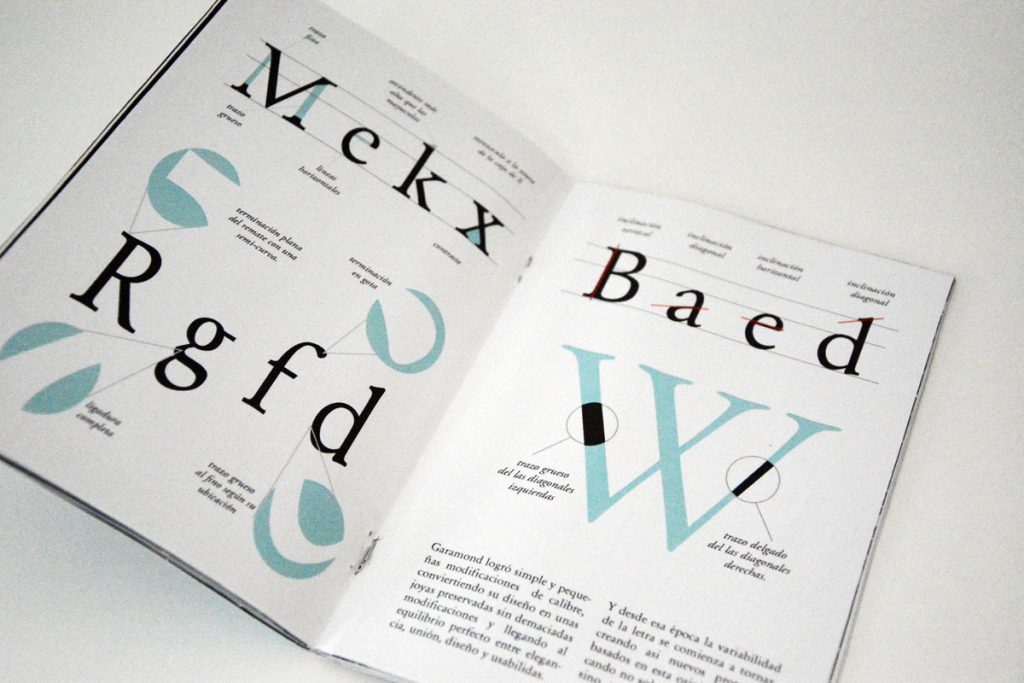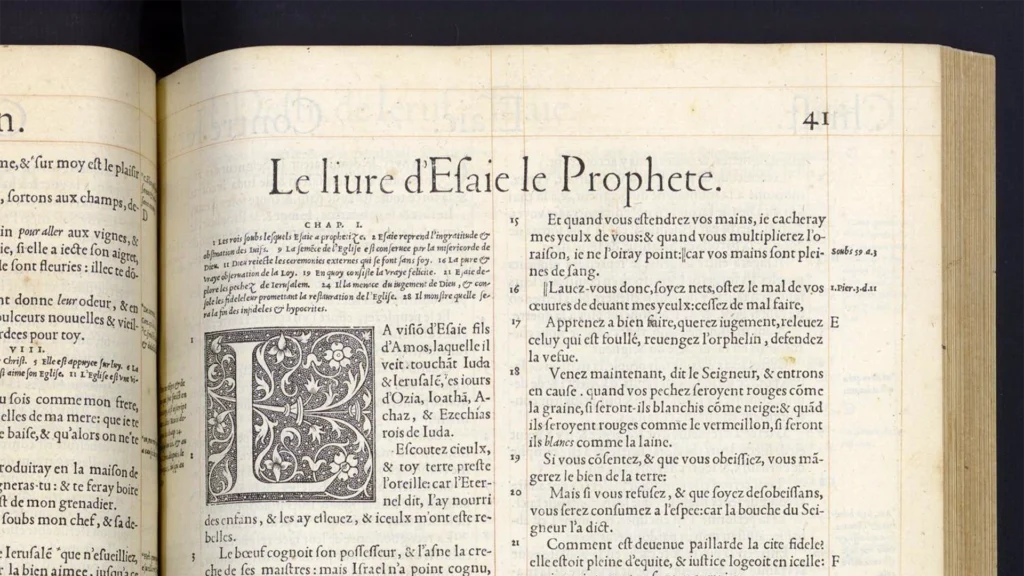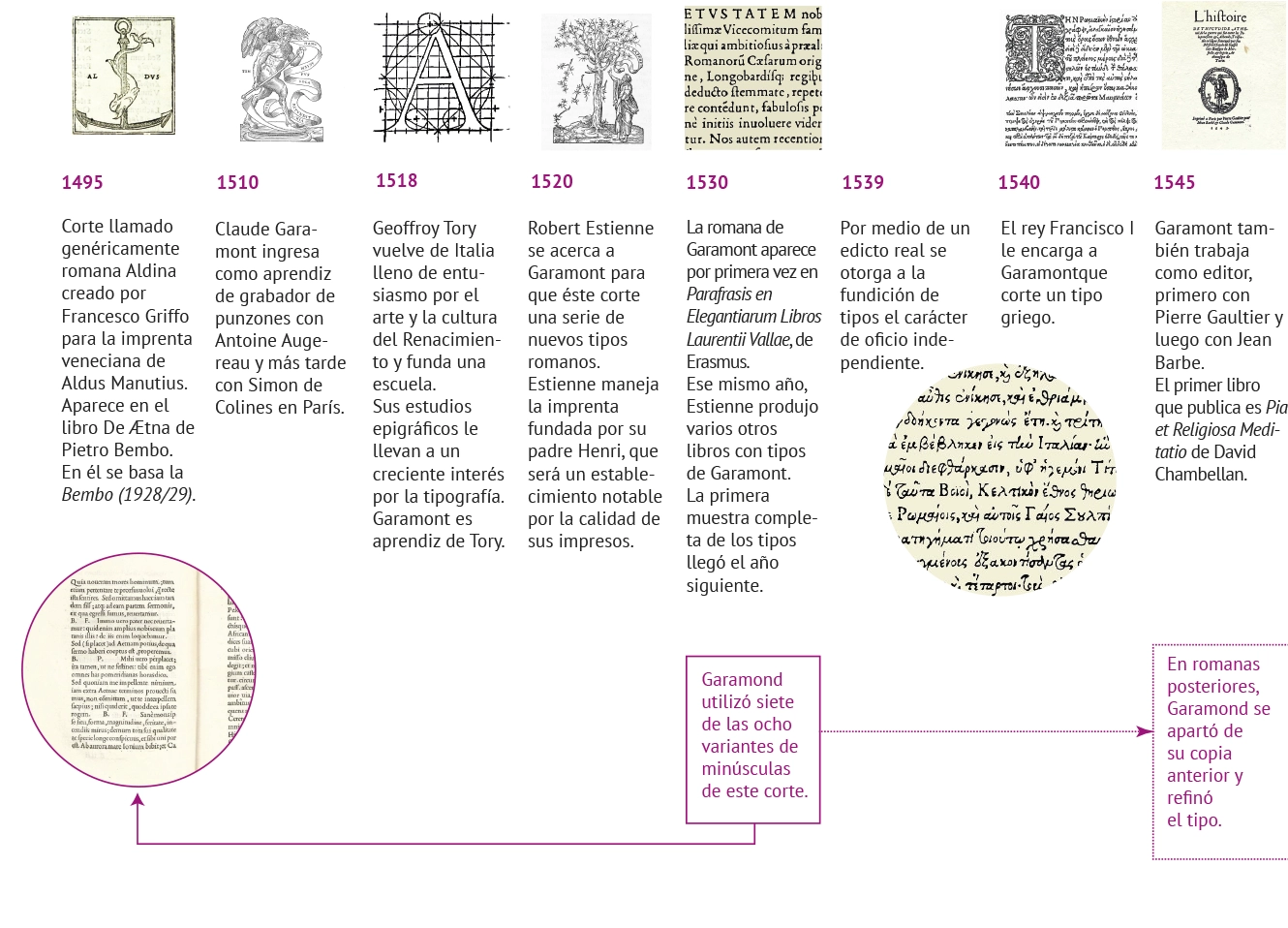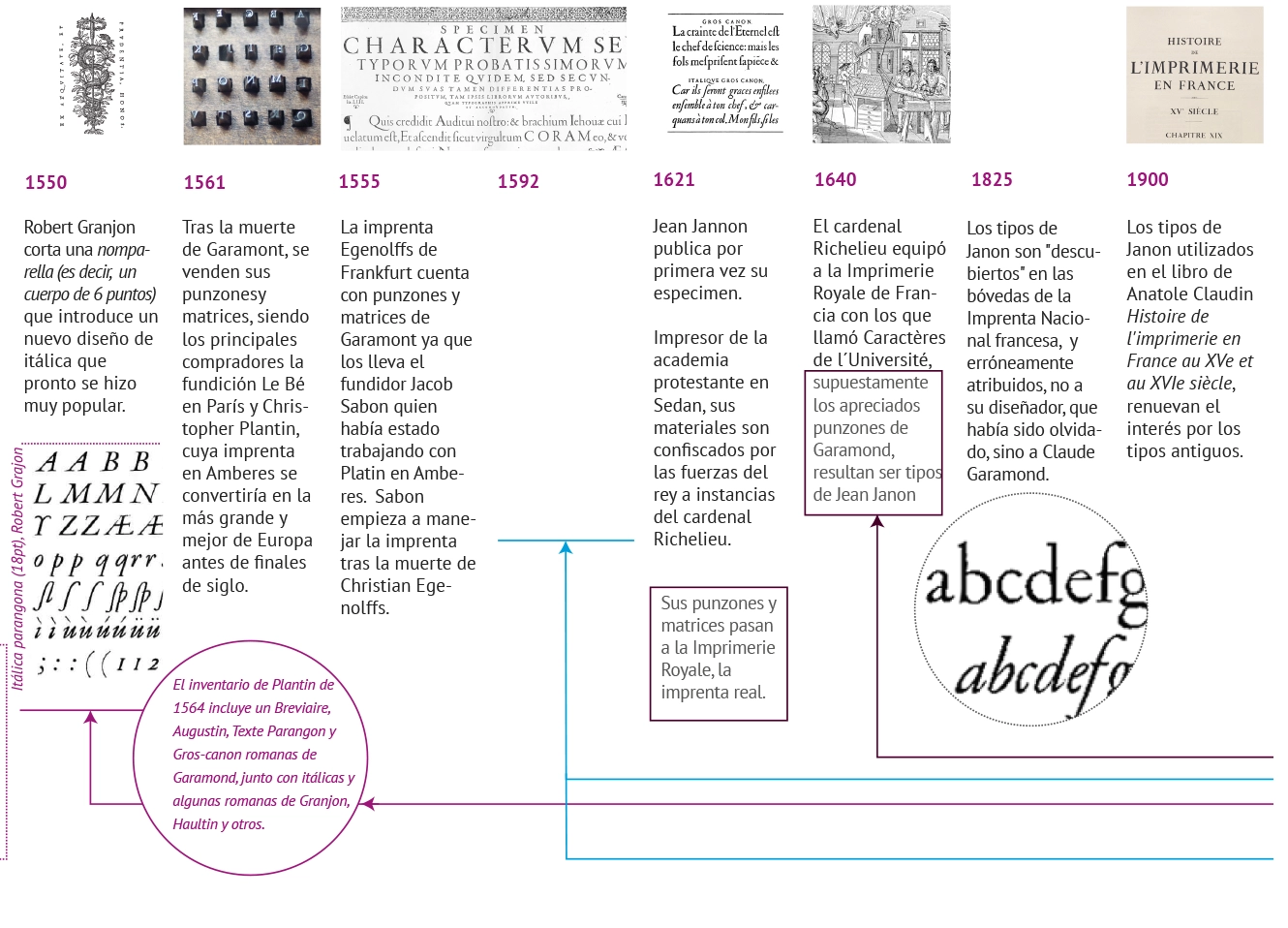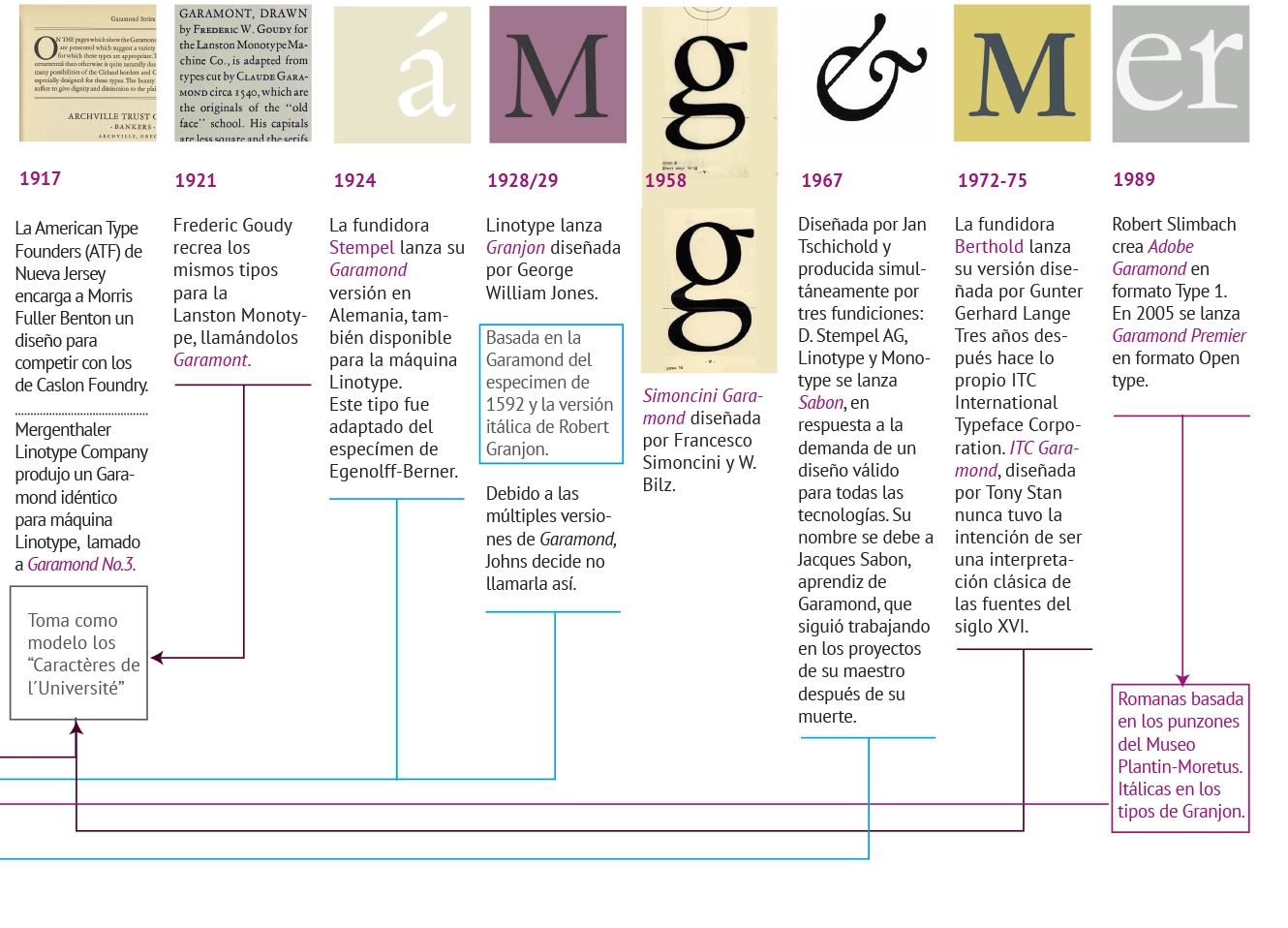
Hay tantas versiones de Garamond que nos es difícil encarar un artículo sin riesgo de dejar afuera información relevante. Aquí intentamos reunir cierta información acerca de su genealogía para dar cuenta de las herencias así como de las traducciones, confusiones y adaptaciones que jalonan su historia.
Garamond
Los tipos que actualmente llevan el nombre Garamond hacen referencia al gran punzonista francés del siglo XVI llamado Claude Garamont. Ha lo largo del tiempo, han tenido siempre gran demanda y, por lo tanto, están disponibles en una variedad de versiones de diferentes fundiciones. Estas muchas versiones no siempre conservan características del original. Esto es un factor que desconcierta y dificulta su identificación tal como se desarrolla en el artículo Garamond vs. Garamond.
En muchos casos, sería más apropiado el término más genérico de Garalda para referirse a estas fuentes. En particular, muchos resurgimientos de Garamond de principios del siglo XX toman como modelo el trabajo de un punzonista posterior a Garamond llamado Jean Jannon. Aunque su trabajo es notablemente diferente durante años fue atribuido erróneamente a Garamond.
Por otra parte, los revivals actuales de Garamond agregan pesos y variantes que ni remotamente existían en el original.
Aún hoy continúan apareciendo nuevas interpretaciones acerca de estas fuentes históricas dando fe que estos diseños siguen ofreciendo un desafío en la búsqueda de sus formas originales.
La historia de la tipografía que conocemos como Garamond es sumamente compleja y con esta línea de tiempo intentamos exponer sus puntos más salientes.
Sobre la línea de tiempo…
:: A partir del 1500, los hábitos de lectura llevaron a los tipógrafos parisinos a invertir en diseñar y cortar nuevos tipos à l’antique. Juegan un rol predominante en este cambio cultural el teórico Geoffroy Tory (1480-1533) que estaba al servicio del rey Francisco I, así como numerosos eruditos y artistas italianos que Francia recibió entre los años 1520 y 1530.
:: Por otra parte, a principios del siglo XVI, la comunidad de impresores franceses se sentía cada vez más atraída por la Reforma Protestante, que priorizaba la lectura de los textos sagrados y su correcta transcripción. Con esta idea en mente, Robert Estienne (1503-1559)2, en París, trabaja para publicar la versión más legible de la Biblia y se dota de un taller tipográfico a la altura de esta misión.
:: No hay duda de que el tipo con el que el famoso impresor veneciano Aldus Manutius publicó De Ætna fue el modelo para estas versiones francesas. Aldus no fue el primero en utilizar el tipo romano en imprenta, pero fue el suyo llegó a ser más influyente. El tipo de De Ætna (después conocido después como Bembo), poseía ocho variantes de ciertas letras minúsculas y en los tipos que cortó Garamont, utilizó siete de estas variantes.
:: Como vimos, Estienne se inspira en los diversos modelos de romanas diseñados por Aldus Manutius y su punzonista Francesco Griffo. Pero estos tipos de letra habían sido relativamente poco desarrollados para diferentes tamaños de texto. El taller de Robert Estienne, va a perfeccionar la obra de Manutius ganando en finura y legibilidad, con un eje ligeramente recto, un mayor contraste entre grueso y fino, contraformas más sutiles y serifas más ligeras.
:: A lo largo de los años, los tipos romanos de Garamond fueron alejándose del modelo original. En cambio, parece haber tenido poco interés en los tipos itálicos «que simplemente se limitó a copiar, no muy bien, el tipo de Aldo Manucio en 1545» (Warde, 1926).
:: Durante mucho tiempo Garamond fue el nombre usado para designar una imitación de una romana y una itálica en posesión de la Imprimerie Nationale de París que eran conocidos como los caractères de l´Université. La tradición asigna la autoría de estos tipos a Garamond. Más tarde se supo que pertencían a Jean Jannon.
:: Existen muchas versiones llamadas Garamond que hacen referencia a los signos cortados por Claude Garamond quien trabajó de forma independiente para distintos impresores, e incluso existen otras que sin llamarse así están basadas en sus formas. Hayan sido diseñadas para la tecnología de impresión que fuera, son producto de una serie sucesiva de interpretaciones como también lo fueron los signos cortados por Claude Garamond.
:: Según la opinión de muchos, la versión más auténtica podría ser la creada por la fundición Stempel en 1924. Está basada en el especímen de la fundidora Egenolff-Berner, con tipos de Garamond. Según las palabras de Simon Loxley: «Es uno de los mejores tipos de letra serif, bellamente balanceado, excelentemente legible, elegante pero al mismo tiempo amigable, una combinación extremadamente difícil de lograr». Otras versiones fieles aunque no llevan el nombre Garamond son la Sabon, desarrollada por Ian Tschichold en 1960 y la Granjon descripta por Beatrice Warde como: «Se trata de una fuente de “color” claro y de diseño delicado pero fácilmente legible ya que no tiene ningún rasgo que distraiga al ojo de la lectura.» Granjon fue diseñada por George W. Jones alrededor de 1924 para la sucursal británica de la empresa Linotype, y se basa en el tipo de letra usado en un libro impreso por el parisino Jean Poupy en 1592. El diseño era de Claude Garamond y la versión en cursiva era de Robert Granjon. Debido a que en la década de 1920 había varios otros Garamond en el mercado, Jones decidió llamar a su tipo Granjon.
:: Otras versiones no tuvieron como objetivo la fidelidad con el original como la Garamond Simoncini o la ITC Garamnod. Esta última fue diseñada por Tony Stan para la International Typeface Corporation (ITC) en 1975 buscando mejorar la legibilidad y satisfacer las necesidades de las impresoras de su tiempo. Por lo tanto, modificó la altura de x, agrandó los ojos (por ejemplo la ‘a’y de l ‘e’ guardan poco que ver con una garalda) y reelaboró el contraste entre gruesos y finos manteniendo la armonía general. También agregó variantes al “inventar” variables bold, light y condensada. El resultado es una ruptura con la Garamond tradicional, más peso y menos elegancia. «Hay buenos y malos revivals, ITC Garamond es de los últimos» (Michael Bierut, 2004). A pesar de la mala opinión de muchos conocedores, ITC Garamond disfrutó de mucha difusión ya que formó parte del paquete oficial de tipografías de Apple Computer en 1984 y durante los siguientes 20 años gozó del respaldo de Apple para luego ser reemplazada de la noche a la mañana por Myriad.